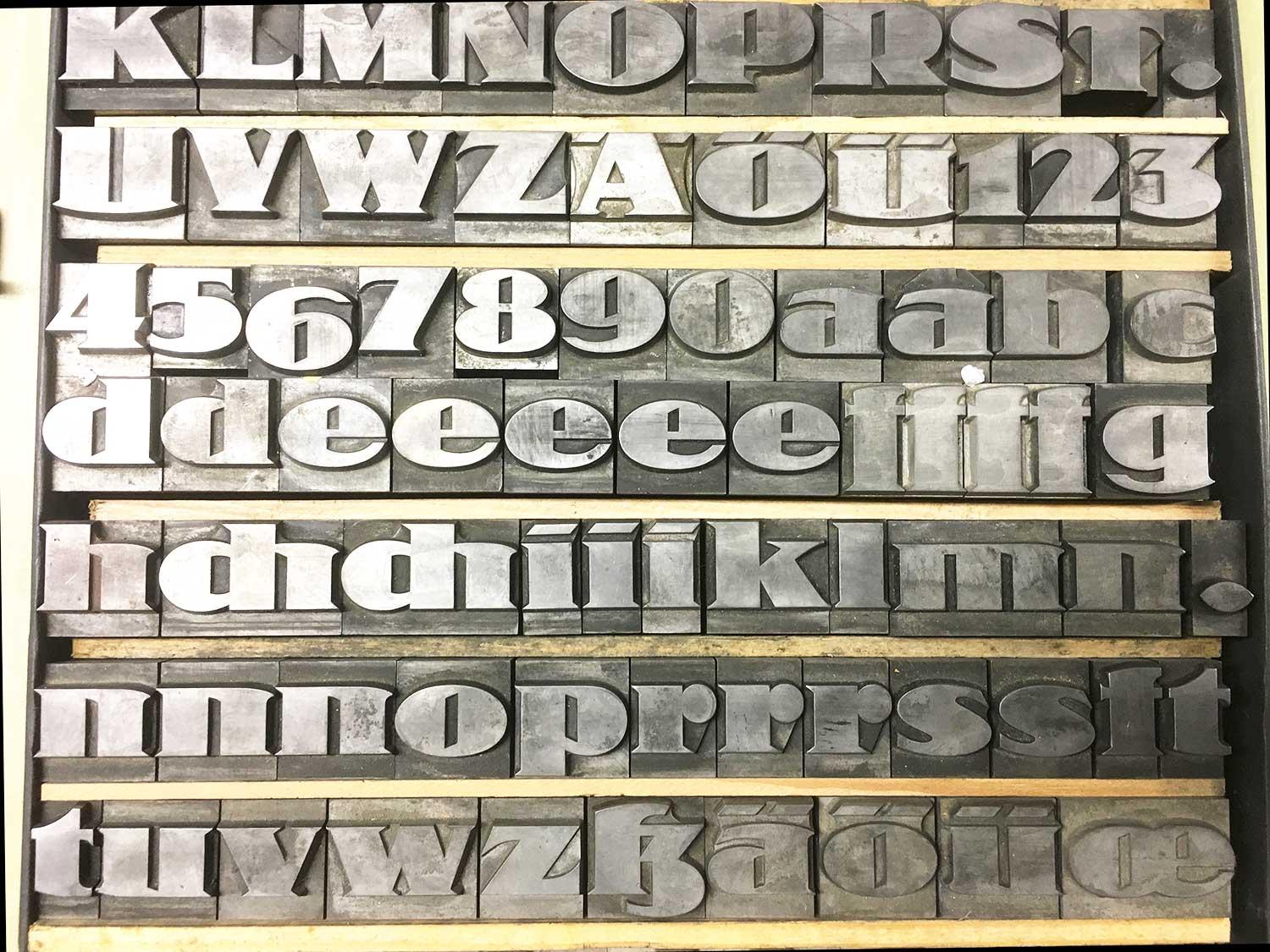
Fette dekorative Bleisatzschrift
a) gibts schon digital?
b)Wenn nein, selbst geplant,
c) wenn nicht, Foto mit A-K?
Zu a) habe ich bei einer kleinen Suche nichts gefunden. Bzgl. Schriftmuster habe ich auch nicht sehr viel finden können. Auch bei fontsinuse war es ziemlich dunkel: https://fontsinuse.com/typefaces/75094/ferrum